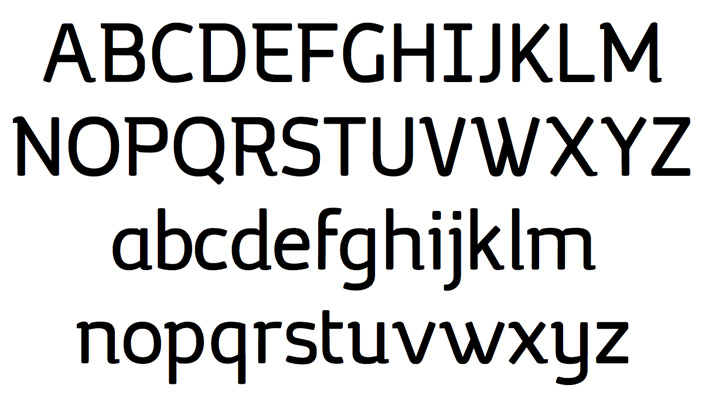
Tipografías gratuitas: Margot ha sido diseñada por Adriá Gómez <http://www.adriagomez.com> para la revista Neo2. Esta tipografía no se puede vender o regalar a terceros. El uso comercial de esta tipografía deberá incluir el siguiente texto legal: “La tipografía Margot ha sido diseñada por Adriá Gómez para la revista Neo2″.
Una tipografía gratuita moderna, vibrante y perfecta para todo tipo de proyectos tipográficos, bien sean logotipos o titulares.
Ha sido creada por Adriá Gómez, diseñador gráfico varias veces galardonado con un premio Laus, entre otros.
Margot Typography designed by Adriá Gómez <http://www.adriagomez.com> for Neo2 magazine. This typeface can’t be sold or given to anybody. The commercial use of this typography should always incluye: “Margot typography designed by Adriá Gómez for Neo2 magazine”.
A free modern typography, vibrant and perfect for all kinds of typographic projects, whether they are logos or headlines.
It has been created by Adriá Gómez, a graphic designer several times awarded with a Laus prize, among others.